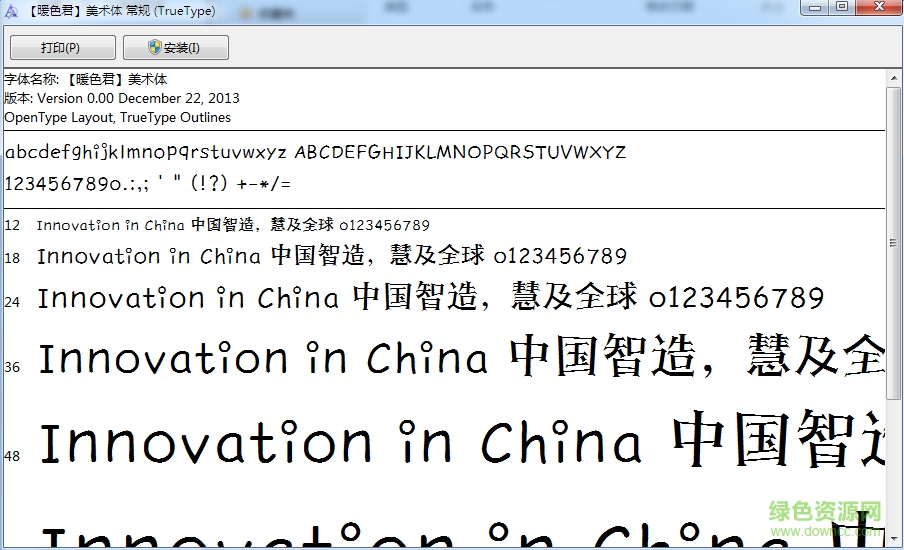
暖色君美術(shù)體字體是一款非常有個(gè)性的美術(shù)字體,可以運(yùn)用到比較廣泛的區(qū)域,使相同的應(yīng)用產(chǎn)生不同的效果,最新最全的英文,簡(jiǎn)繁體字庫(kù),有需要的朋友歡迎來(lái)綠色資源網(wǎng)下載體驗(yàn)!
暖色君美術(shù)體字體是一款該字體瀟灑俊逸、自然舒展、賞心悅目,看上去十分美觀,整體效果非常統(tǒng)一,且字庫(kù)完整,可以廣泛應(yīng)用于名片設(shè)計(jì)、新聞媒體、宣傳海報(bào)、ppt、影視制作以及任何使用文字的領(lǐng)域。